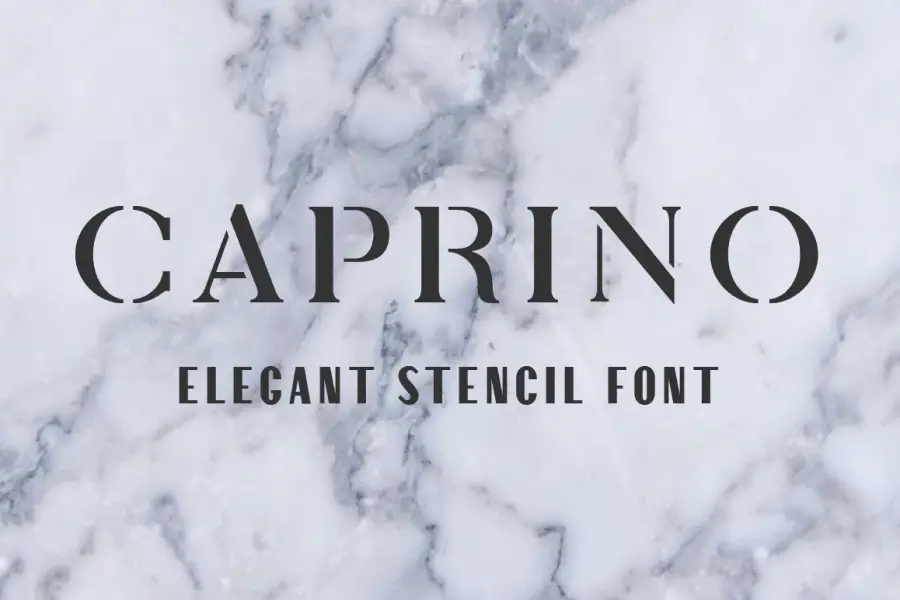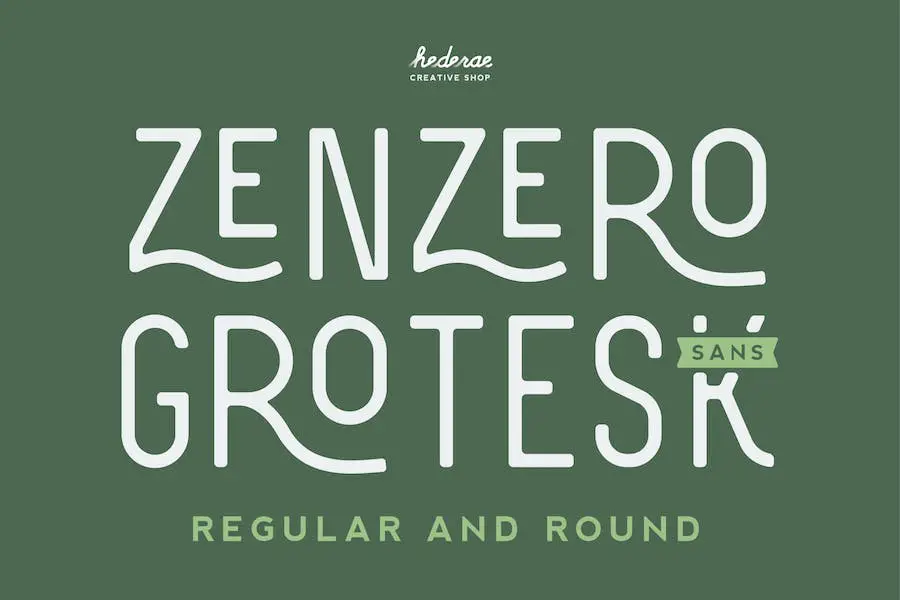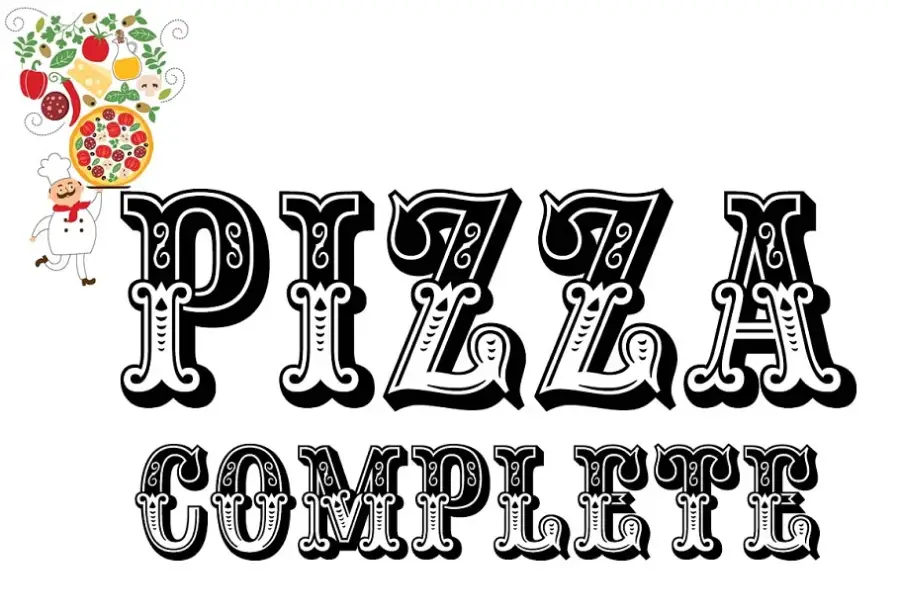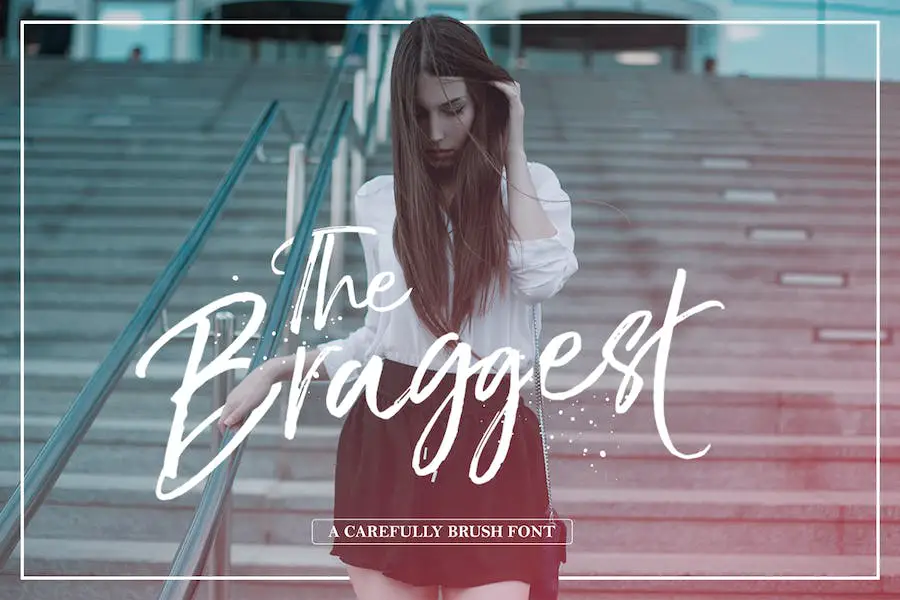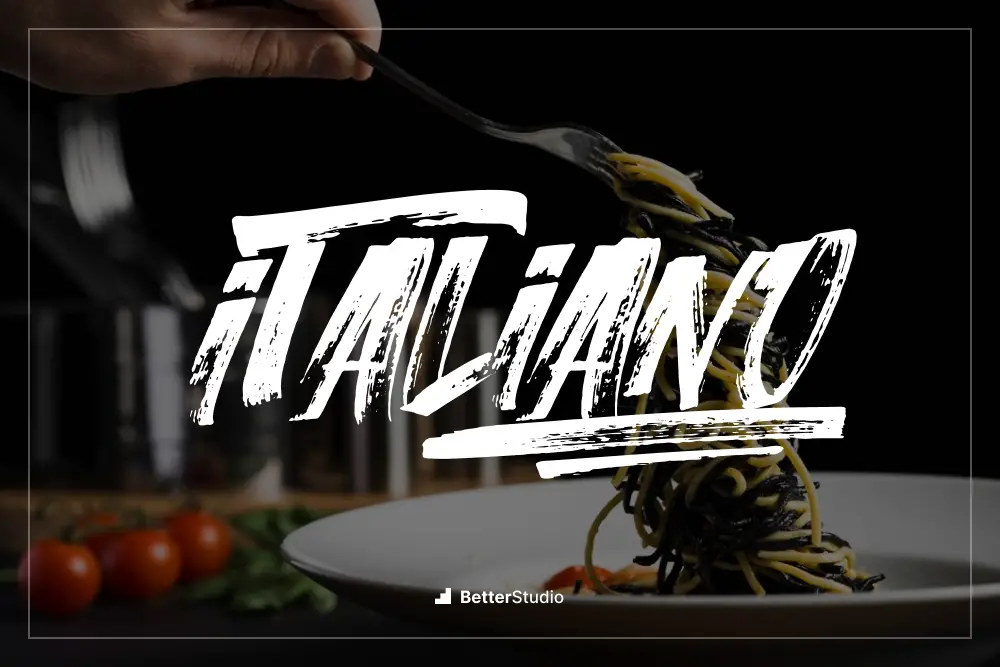
I 15 migliori font italiani del 2023 (gratuiti e premium)
Pubblicato: 2023-04-13Sei mai stato sopraffatto da tutti i font italiani là fuori?
Il carattere perfetto per un progetto può essere difficile da scegliere. È importante se sei un imprenditore che cerca di apparire professionale o un designer che cerca di fare una dichiarazione.
I caratteri italiani sono noti per la loro classica eleganza e raffinatezza. Possono davvero dare vita al tuo progetto con dettagli intricati e abbellimenti decorati. Molti di loro risalgono a secoli fa, quindi portano con sé connotazioni storiche che rendono qualsiasi opera ancora più affascinante. Ci sono così tanti stili e varianti, ognuno con il suo
Ce n'è per tutti i gusti, da quelli di ispirazione vintage a quelli moderni e minimalisti: scegli il font italiano giusto per il tuo prossimo progetto e dai al tuo lavoro un'atmosfera italiana senza tempo.!
Ecco 15 font italiani belli e funzionali.
Migliori Font Italiani Premium
Ecco alcuni dei migliori font premium italiani oggi disponibili, le loro qualità uniche, dove trovarli e come usarli.
Preparati a esplorare alcune delle migliori tipografie italiane e crea fantastici design con font premium italiani!
MOZA
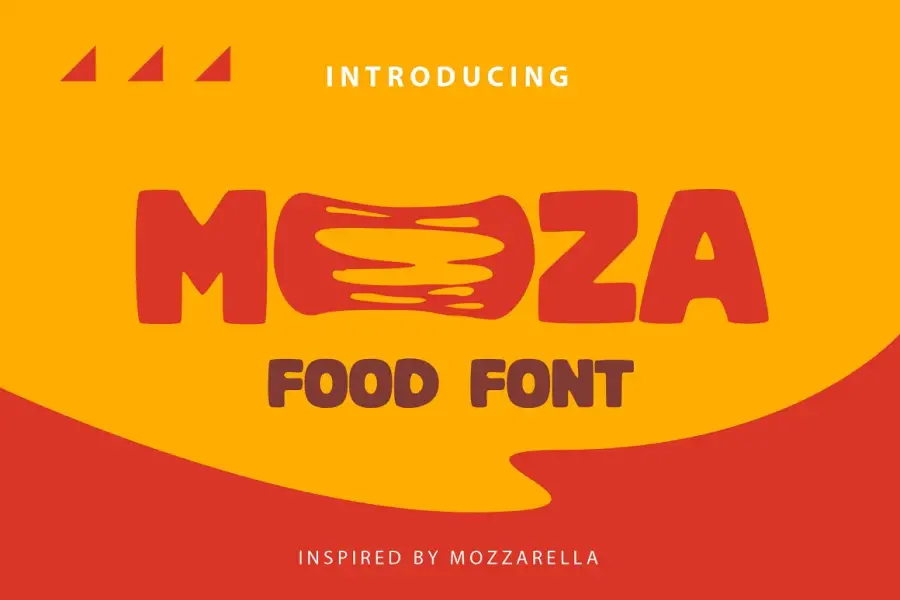
Con lettere maiuscole e minuscole, supporto multilingue, numeri e punteggiatura, MOZA è il font perfetto per la prossima volta che lavori a un progetto legato al cibo.
Le lettere maiuscole di MOZA sono forti e audaci, conferendo a qualsiasi progetto un aspetto nitido e professionale. Anche piccoli dettagli come numeri e segni di punteggiatura possiedono lo stesso stile, consentendo coerenza indipendentemente dal tipo di testo che devi creare.
Il supporto multilingue significa che questo font può essere utilizzato in una varietà di lingue, quindi è perfetto per progetti globali.
Cavallo Italiano
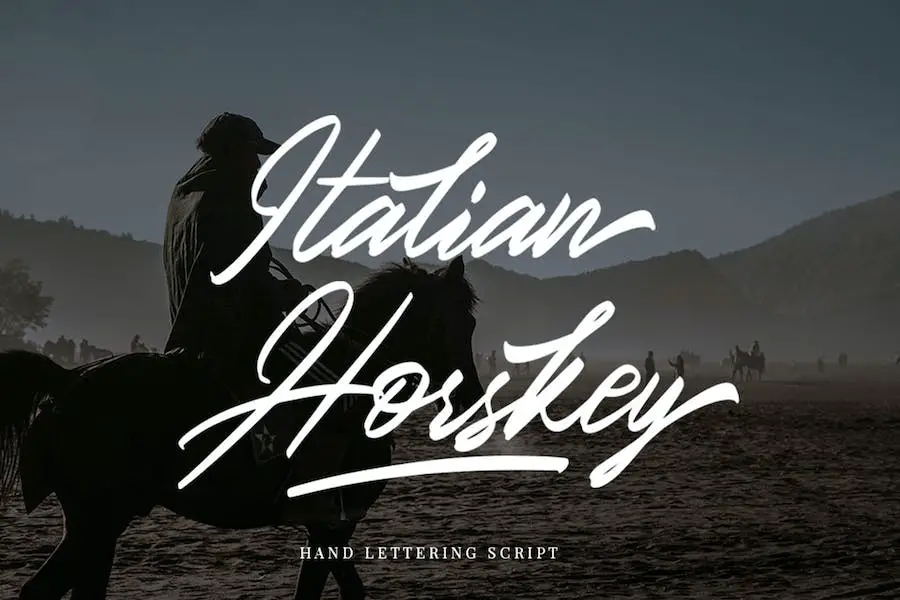
Puoi utilizzare lo script di scrittura a mano della firma Horskey italiana per qualsiasi cosa. I suoi accenti contemporanei e sofisticati nelle sue lettere maiuscole lo rendono una scelta di design ideale. È ottimo per loghi, branding, matrimoni, post sui social media e altro ancora. Lo script Italian Horskey Signature Handlettering offre una bellissima armonia tipografica, indipendentemente da ciò di cui hai bisogno.
Oltre all'elegante aspetto della calligrafia e ai bellissimi accenti, è un'ottima scelta per i caratteri italiani per le parole. Inoltre, ha un sacco di caratteri e legature alternativi in modo da poter creare le tue lettere. Con lettere minuscole fluide, si aggiunge all'aspetto generale.
Fast food
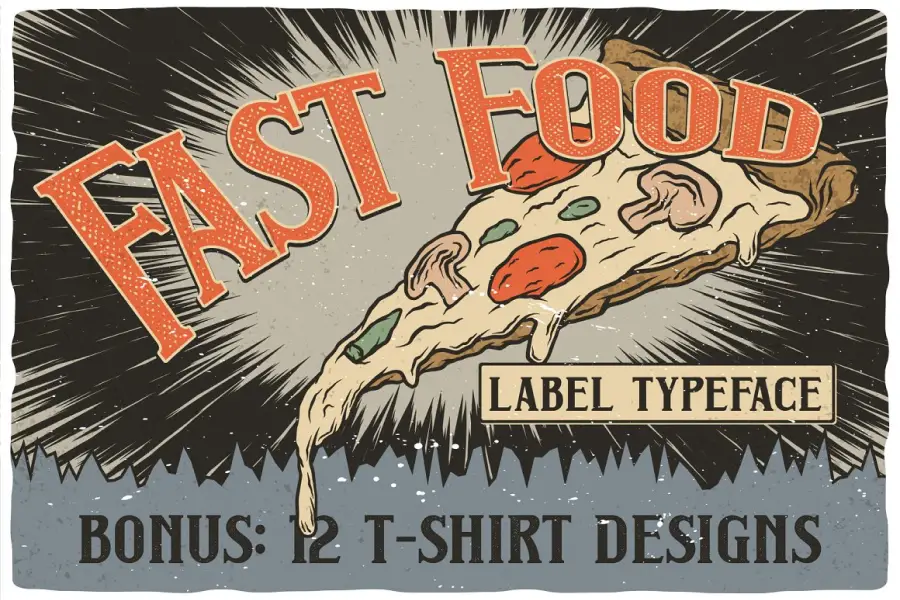
Fast Food è un font per etichette vintage perfetto per scritte sorprendenti su poster, magliette, biglietti di auguri, loghi e altro ancora. Include illustrazioni di classici fast food come hamburger, pizza, piatti wok, hot dog, ciambelle, patatine fritte e tazze. Tutti i design sono isolati, insieme a testo modificabile e due modelli senza soluzione di continuità: colore e monocromatico.
Ti interessa aggiungere un po' di vita ai tuoi progetti? Fast Food potrebbe essere il font che fa per te. Fast Food avrà sicuramente un impatto, indipendentemente dall'uso che ne fai. Ha illustrazioni dettagliate che danno un senso di nostalgia senza essere eccessivamente kitsch e lettere audaci che gli danno forza e sicurezza.
Pesto
In Pesto troverai caratteri sans-serif normali e leggeri e una varietà di caratteri alternativi. Perfetto per loghi, branding, arte, poster o qualsiasi altro progetto creativo, Pesto è fantastico. È possibile digitare lettere maiuscole e minuscole, numeri e simboli, oltre a caratteri alternativi.
Il pesto è super versatile poiché può essere utilizzato in molte lingue. Il pesto ha curve morbide e linee delicate, quindi puoi usarlo per il branding o un carattere tipografico elegante da usare regolarmente come i caratteri italiani per Figma. Vale la pena dare un'occhiata al pesto, sia che tu stia cercando un marchio o un carattere tipografico elegante da utilizzare regolarmente.
Pecorino
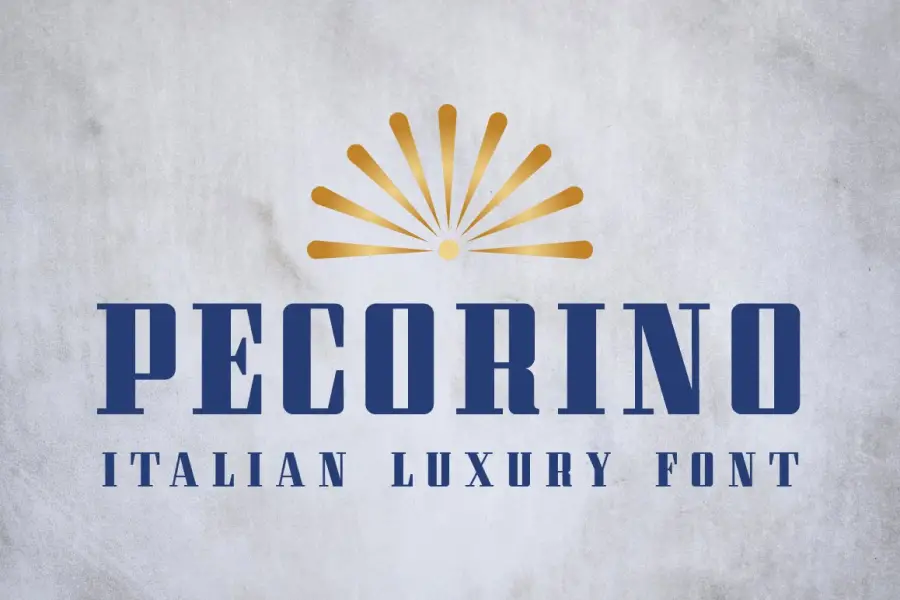
È facile da usare, poiché tutti i componenti si uniscono perfettamente e possono essere manipolati per creare una grafica accattivante. Pecorino offre una gamma di pesi e stili, offrendo ai designer più opzioni durante la creazione di loghi, titoli e altri elementi di testo.
Inoltre, il pecorino è abbastanza versatile da funzionare sia per i progetti digitali che per quelli stampati, rendendolo una risorsa di design incredibilmente utile. Nel complesso, Pecorino è uno dei famosi caratteri italiani che aggiungono un elemento di finezza a qualsiasi progetto.
Lastra Enyo
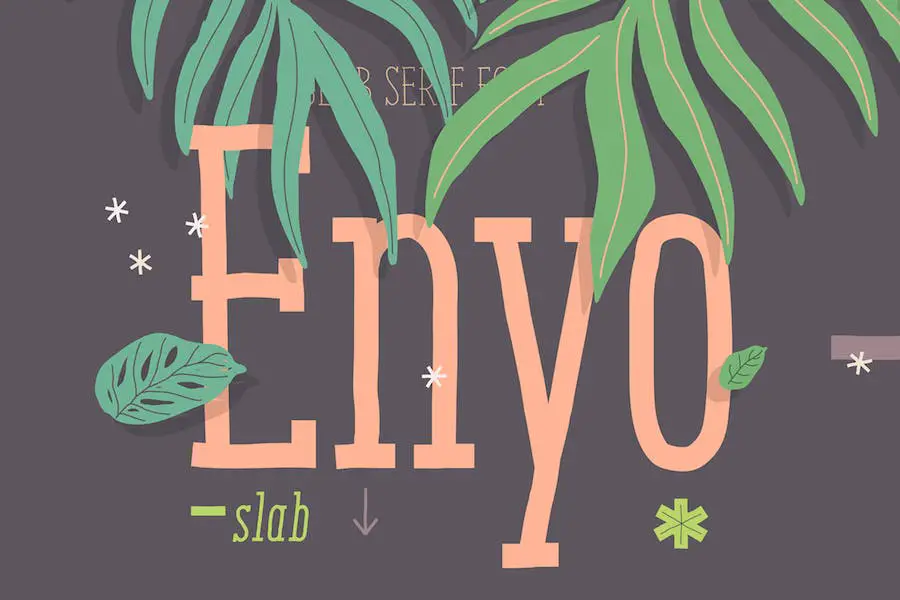
Enyo Slab è un font slab in stile display che aggiunge un tocco informale al tuo lavoro. È perfetto per piccole quantità di testo o per fare una dichiarazione con i suoi glifi di alta qualità. Con Enyo Slab, aggiungi personalità e dinamismo a tutti i tuoi progetti e documenti
Il design è perfetto per creare loghi, titoli e altri display accattivanti. Inoltre viene fornito con oltre 500 caratteri, incluse lettere e legature alternative, così puoi fare quello che vuoi.